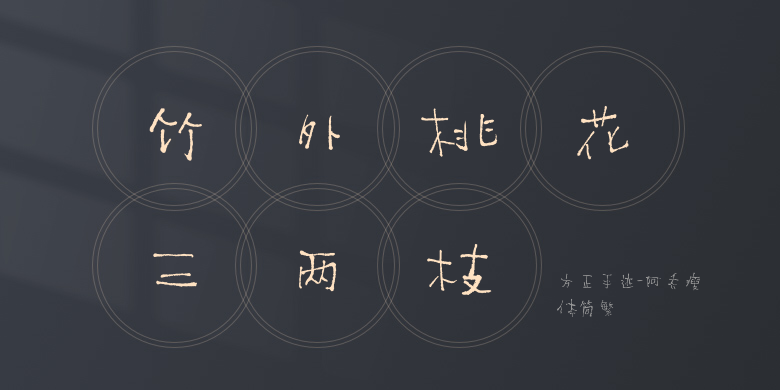
方正手迹-阿乔瘦体简繁
方正手迹-阿乔瘦体简繁,这款字体结构工整、笔画清晰,兼顾美观与易读性,适用于标题、正文、海报、包装、LOGO 等多种场景。字形优雅稳定,风格百搭耐看,适配日常排版与创意设计,让文字呈现更舒适、更具质感。方正手迹-阿乔瘦体简繁一笔一画,皆是细节,以均衡的比例、流畅的线条打造舒适视觉体验,字形端正大气,风格简约现代。无论是商业设计、品牌宣传还是日常排版,都能轻松驾驭,让文字更有格调与力量。方正手迹-阿乔瘦体简繁字体下载。